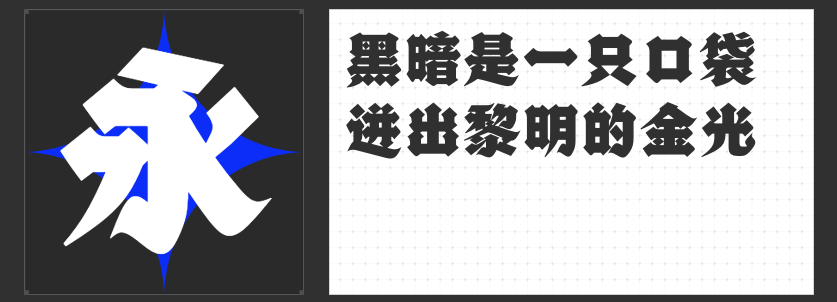
游戏视觉革命:四款风格化字体重塑玩家沉浸体验
在游戏设计的视觉战场中,字体不仅是信息载体,更是构建世界观、强化情绪共鸣的核心元素。从硬核格斗的金属质感,到奇幻冒险的魔法韵律,以下四款专业级字体以独特的设计语言,为不同类型游戏注入灵魂级视觉表现。
一、励字铁拳简 超级黑
这款专为竞技类游戏打造的创意黑体,以120%字面率构建出碾压级的视觉存在感。粗壮如钢筋的笔画搭配圆角折角设计,既保留了黑体的机械理性,又通过柔和过渡消解了攻击性。
二、励字跨界黑简 超级黑
通过90%字面率与夸张笔粗的矛盾统一,这款字体在科幻题材中展现出惊人适应性。向上微抬的钩笔画与斜切收尾形成视觉引导线,既保持军工级严谨,又暗含跃迁引擎的动感。特别设计的负空间布局,能解决传统粗黑体在小尺寸下的可读性难题。
三、高手字斋哥特体Pro
突破传统哥特体的长形结构,这款等宽字体以1:1的黄金比例重构神秘符号。锋利如刀的笔画与平滑曲线形成强烈对比,又通过微曲弧度暗示灵力流动。特别优化的竖排排版系统,使门派技能树呈现古籍装帧的仪式美感,符号库中的图腾笔画更可直接调用为法术特效素材。
四、字恋狂丸粒简
通过全圆角处理与30%笔画加粗,这款字体为休闲游戏开辟了新美学维度。圆头圆尾的字符随角色情绪产生弹性变形,配合2.5D光影渲染,创造出"文字会呼吸"的交互体验。其内置的200+表情符号库,更支持开发者通过简单参数调整生成专属萌系字体变体。
这四款字体通过结构力学与情感设计的深度融合,重新定义了游戏字体的价值维度——它们不仅是视觉元素,更是连接玩家与虚拟世界的神经接口。